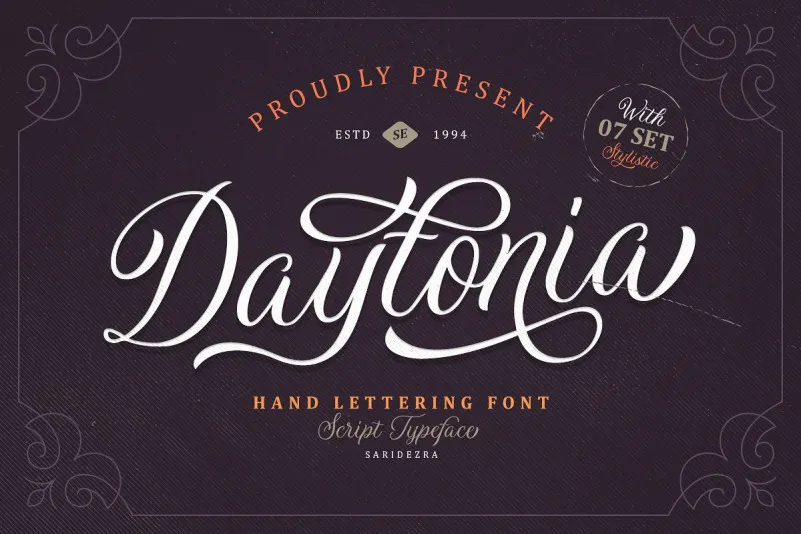
Daytonia Script Font
Daytonia Script Font é uma nova aquisição para seu arsenal de letras feitas à mão. A M.0Type apresenta Daytonia, um script-font moderno e sofisticado, projetado por Sarid Ezra especialmente para atender às necessidades de designers gráficos. Ideal tanto para aplicativos de marca, como logos e arte digital, quanto para criações em letras manuscritas, Daytonia Script é uma escolha versátil. Suporte multilinguagem, numeração e símbolos permitem criar designs variados. O alternativo, acentuação e sublinhado oferecem ainda mais personalidade ao seu trabalho. Seja para um projeto de marca ou para ilustrações manuscritas, Daytonia Script é uma opção segura de qualidade que se destaca em qualquer ambiente de design. Não hesite em explorar os infinitos recursos criativos que essa font pode lhe oferecer.